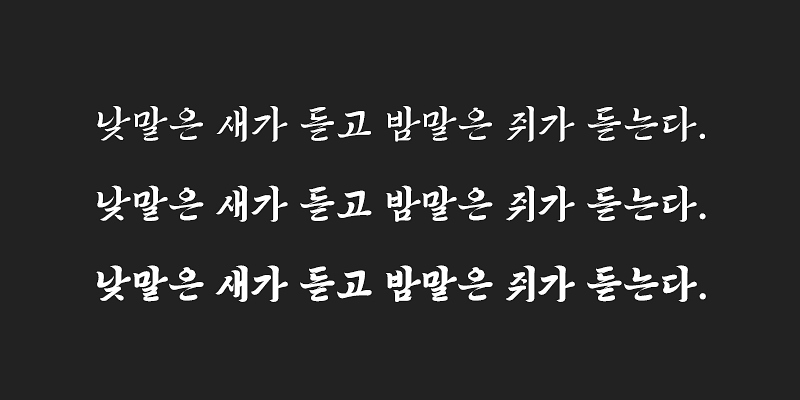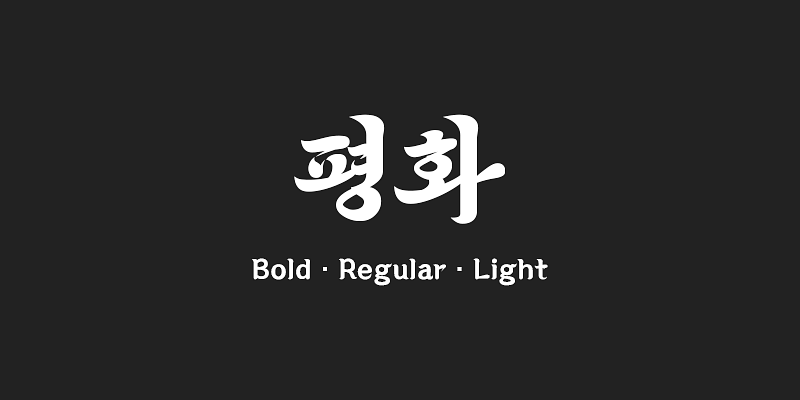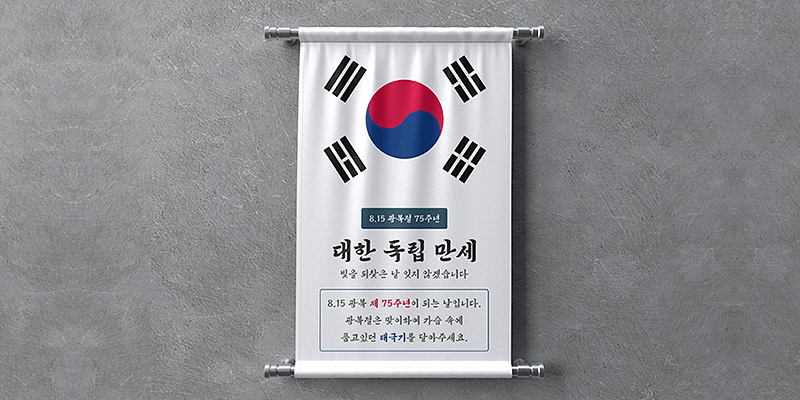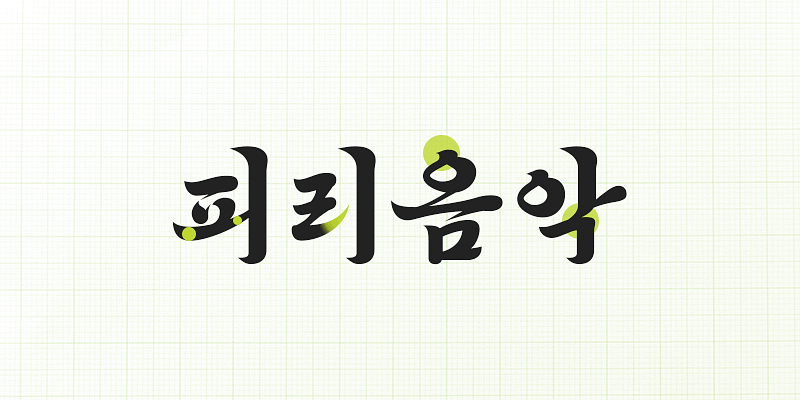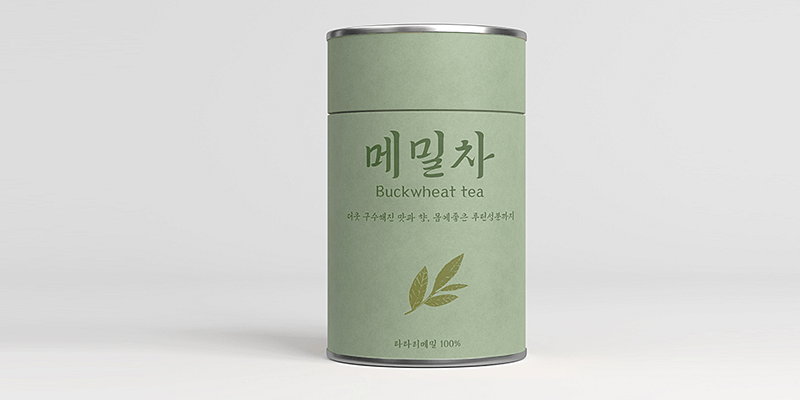
210 Pyeonghwa est une police basée sur la calligraphie coréenne au pinceau à l’ancienne. La variation de la pression et de la vitesse d’écriture se reflète dans le design, ce qui donne à la police un aspect dynamique et féroce. Des formes légèrement irrégulières ont été incluses intentionnellement pour accentuer le sentiment de rudesse et d’ancienneté.